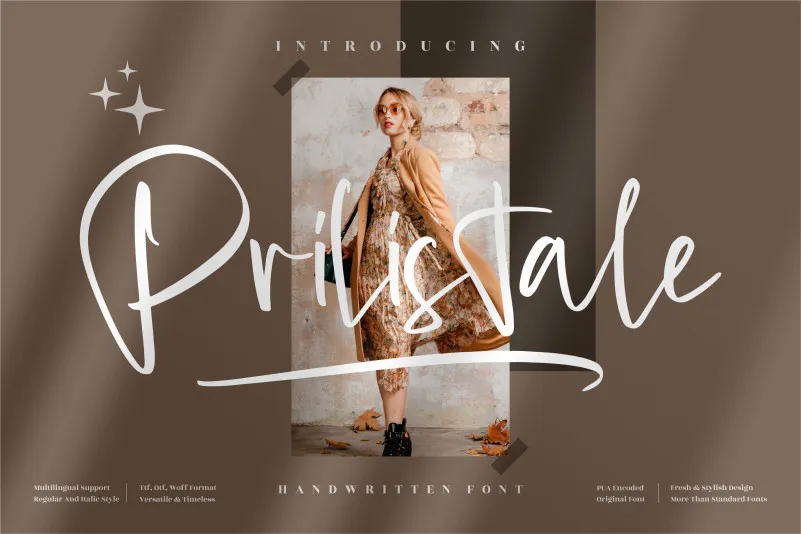
Prilistale Font
A Prilistale Font é uma elegante fonte que captura a essência delicada do estilo manuscrito, perfeitamente adaptada para os projetos mais luxuosos e criativos. Suave e autêntica, esta fonte vai além das simples letras digitais, oferecendo um toque único e pessoal a qualquer trabalho. Perfeita para criações que valorizam o design natural e autoral, ela pode ser encontrada em uma ampla variedade de projetos, incluindo logos e marca, embalagens de produtos, mugs personalizados, cartões de convite, revistas e livros, etiquetas para embalagens, fotografias customizadas ou até mesmo marcas para eventos especiais. A Prilistale é a escolha perfeita para quem deseja dar um toque especial e único a seus projetos, garantindo que sua mensagem seja escrita de uma maneira única e memorable.